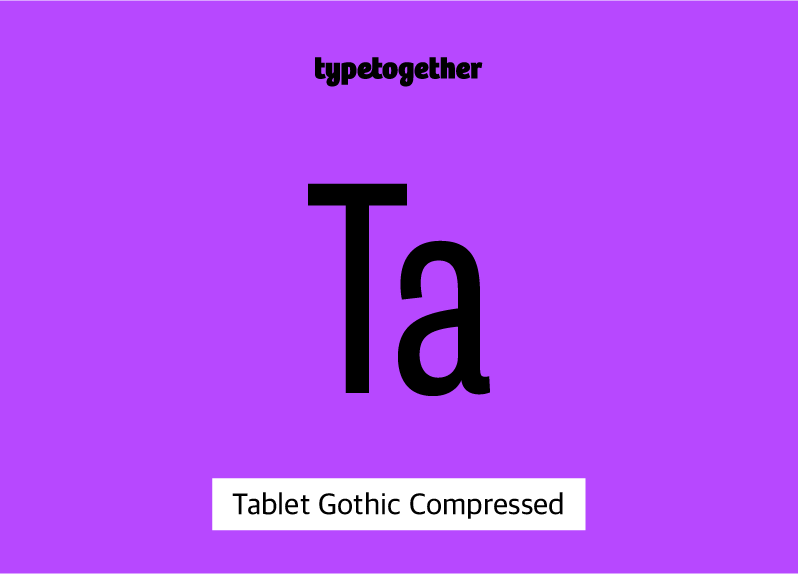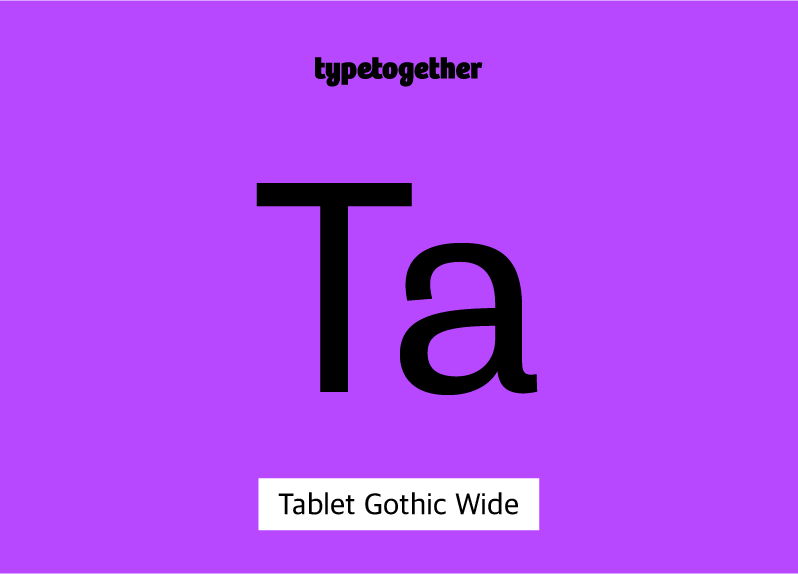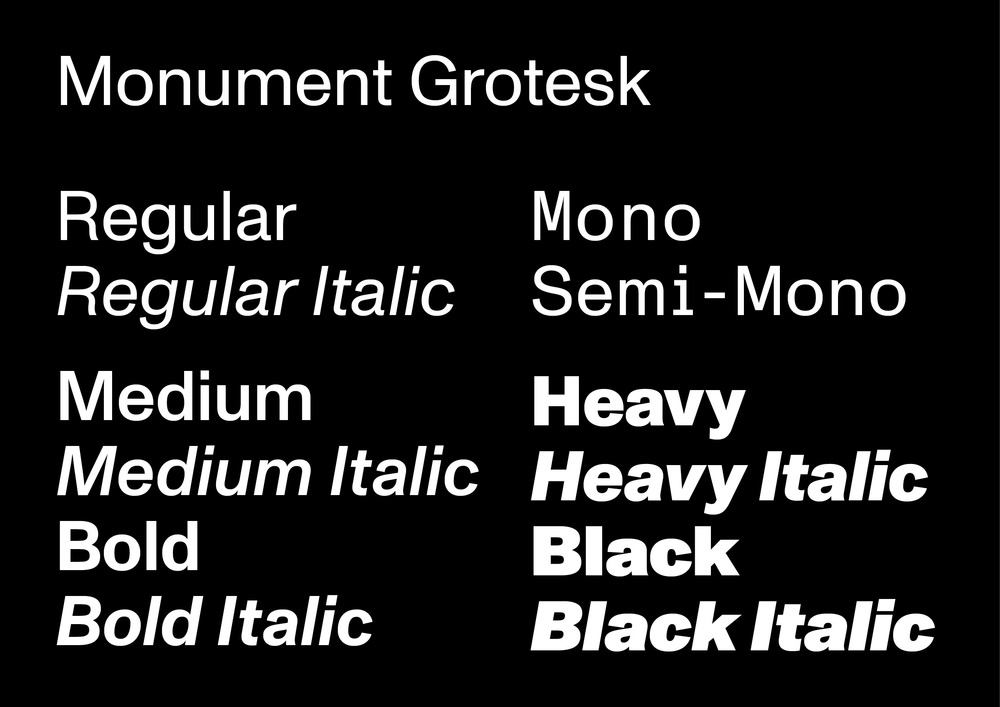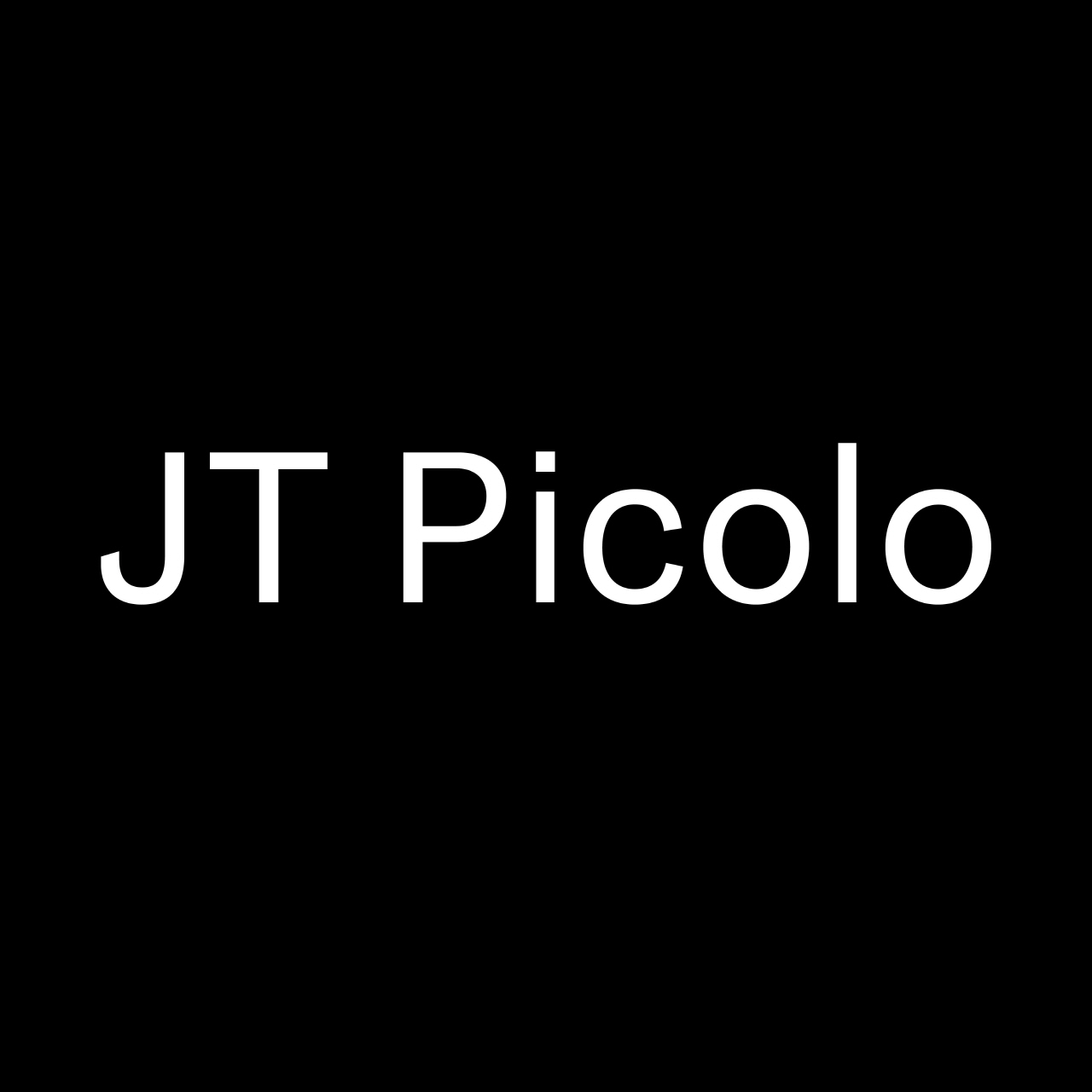
깔끔한 디자인의 완성
뉴트럴한 라틴 산세리프 폰트 추천
살면서 딱 하나의 폰트만 쓸 수 있다면?
많은 분들이 비슷한 폰트를 떠올리셨을 것 같은데요.
혹시 깔끔하고 질리지 않는 산세리프 폰트를 선택하지 않으셨나요?
산세리프 폰트 하나만 잘 골라도 디자인이 쉽게 완성되는 걸 느껴보셨을 거예요.
중립적인 인상이라 다 똑같다는 생각은 금물! 뉴트럴한 폰트들도 미세한 차이로 각기 다른 매력을 발산하는데요.
산돌구름에서 특별히 엄선한 폰트들을 지금 소개해 드릴게요.
네오-그로테스크가 뭐지?
오늘 소개할 폰트들은 네오-그로테스크(Neo-Grotesque)라는 계열로 분류되는 라틴 폰트들입니다.
글자의 장식적이거나 투박한 요소를 다 덜어내고 정제하여 깔끔한 인상이 특징이죠.
대표적인 폰트로는 헬베티카(Helvetica), 유니버스(Univers), 에리얼(Arial) 등이 있는데요.
산돌구름에서 만나볼 수 있는 현대적인 인상의 네오-그로테스크 계열 폰트를 알아볼까요?
디나모
ABC Monument Grotesk
「ABC Monument Grotesk」는 스위스 파운더리 디나모에서 만든 폰트입니다. 디나모는 2016년에 스위스 연방 문화청으로부터 스위스 디자인 어워드를 받을 정도로 실력을 인정 받았고, 국내에서도 많은 팬을 보유하고 있어요. 「ABC Monument Grotesk」 는 디나모의 초기 설립 때부터 함께한 대표 폰트 중 하나랍니다.
「ABC Monument Grotesk」는 출판물, 사이니지, 포스터, 패키징 등등 매체와 사이즈를 가리지 않고 두루두루 쓰이고 있습니다. 별다른 그래픽 요소 없이도 글자의 형태와 리듬감 자체를 한껏 살린 디자인에 특히나 멋지게 어울려요. 각 글자들은 정직하고 개성 넘치는 형태를 특징으로 하며, 전형적인 네오-그로테스크 계열보다 약간 더 강조된 획대비가 매력적인 질감을 선사합니다. 하지만 모든 글자 전반의 조화로운 균형이 안정적인 글줄을 형성하여 모던한 인상을 줍니다. 폰트 하나만으로 전체 디자인의 완성도를 확! 높혀주는 것을 확인할 수 있죠.
고정폭 버전인 「ABC Monument Grotesk Mono」와 고정폭 폰트의 디자인 컨셉을 차용했지만 사실 완전한 고정폭 서체는 아닌 「ABC Monument Grotesk Semi-Mono」 패밀리도 있어 더욱 다양한 룩에 맞게 활용할 수 있는데요. 모노스페이스의 기계적인 느낌은 살리면서도 본문 조판에도 적합한 폰트를 찾고 있다면, 「ABC Monument Grotesk Semi-Mono」를 한 번 활용해 보시는 것을 추천드립니다.
플레이타입
Studio6
「Studio6」는 덴마크 파운더리 플레이타입에서 제작한 네오-그로테스크 산세리프 폰트입니다. 이 폰트는 획의 끝 부분이 수직 수평으로 깔끔하게 잘리도록 처리되어 더욱 정돈된 느낌을 줍니다. 로만과 이탤릭 각각 9종의 굵기를 제공하여 총 18종의 탄탄한 구성을 갖춘 패밀리랍니다.
이 폰트는 작게 보면 모든 획의 굵기가 균일해 보이지만, 크게 자세히 보면 획과 획이 만나는 부분이 미세하게 좁아지도록 디자인된 것을 볼 수 있어요. 이는 작은 크기에서는 획이 뭉쳐 보이는 것을 방지하고, 큰 크기에서는 독특한 디자인 요소로 작용할 수 있는 매력적인 디테일입니다.
다양한 패밀리 구성
네오-그로테스크 폰트는 다양한 너비와 굵기를 갖춘 방대한 패밀리로 사용자들에게 폭넓은 선택권을 제공하며 큰 인기를 얻었습니다. 다양한 용도에 맞게 활용할 수 있어, 프로젝트에 맞는 최적의 선택을 할 수 있도록 도와줍니다.
산돌구름에도 이렇게 다양한 패밀리를 갖춘 폰트들이 많이 있는데요. 한번 살펴볼까요?
더타입파운더스
Shapiro
「Shapiro」는 더타입파운더스에서 제공하는 폰트로, 7개의 서브 패밀리로 나뉘어서 제공되는데요. 패밀리의 이름을 자세히 보면 각기 특화된 용도에 알맞게 디자인 되어 있다는 것을 알 수 있습니다.
기본 버전인 「Shapiro」는 자간이 적당히 넉넉하게 적용되어, 작은 사이즈에 긴 글줄로 조판했을 때도 갑갑해 보이지 않아 본문용으로 쓰기에도 알맞은 패밀리에요. 「Shapiro Headline」과 「Shapiro Display」는 좀 더 큰 크기의 헤드라인이나 디스플레이 용도로 사용되기 적합하도록 자간이 조금 더 좁게 조정된 패밀리입니다. 글자의 수가 적다면, 자간을 좁게 설정하는 것이 덩어리감을 더해 주어 주목성을 높일 수 있기 때문이죠. 「Shapiro Max」는 이런 좁은 자간을 최대치로 적용하여, 공간을 아주 큰 크기의 글자로 채워야 할 때 쓰일 수 있도록 설계했어요.
「Shapiro」는 위에 소개한 패밀리 외에도 굉장히 두꺼운 굵기 2종을 제공하는 「Shapiro Base」, 넓은 폭의 「Shapiro Wide」, 그리고 좁은 폭의 「Shapiro Pro」까지 다양한 서브 패밀리들로 구성되어 있어요. 베리어블 폰트로도 만나볼 수 있으니, 미세한 웨이트 조절이 가능해 훨씬 더 유용하게 쓸 수 있답니다. 선택의 폭은 무궁무진하겠죠?
타입투게더
Tablet Gothic
「Tablet Gothic」은 사용자들의 눈에 가장 익숙한 비율일 「Tablet Gothic Wide」 부터 매우 좁은 너비의 「Tablet Gothic Compressed」 까지 무려 6개의 다양한 너비를 제공하는 폰트 패밀리인데요. 한정된 공간에 많은 양의 정보를 조판해야 한다면 특히나 유용하게 사용할 수 있는 폰트입니다.
「Tablet Gothic」은 차갑고 정제된 느낌의 네오-그로테스크보다는 약간 따뜻하고 투박한 느낌을 가진 초기 그로테스크 인상을 지니고 있는 폰트입니다. 대문자 I 가 위아래로 세리프를 가지고 있는 형태이고, 글자가 시작되는 상단 획의 끝부분이 약간 안으로 말려 들어간 대문자 G, C 그리고 소문자 r, a 등의 형태가 생동감을 더해줍니다.
이 폰트는 긴 글에 쓰였을 때 특히나 그 따뜻한 질감과 특유의 매력이 더 잘 느껴진답니다. 특히 다양한 위계가 필요한 잡지 등의 편집 디자인에서 빛을 발할 폰트입니다. 강조가 필요한 곳에는 두꺼운 굵기로, 소제목은 좁은 너비와 대문자의 조합으로 조판해 보는 건 어떨까요? 통일된 느낌을 주면서 지면에 풍부한 느낌을 더할 수 있을 거에요. 「Tablet Gothic」 은 특히 숫자도 매력적으로 디자인되어 있어, 디자인 요소로 꼭 활용해 보시길 권해드립니다.
더 특별한 것을 찾고 있다면?
기본적인 형태는 중립적인 인상을 가지고 있지만, 어딘가 독특한 포인트가 있는 폰트를 찾고 있다면 주목해 주세요.
줄라이타입
JT Picolo
「JT Picolo」는 7월에 새롭게 입점한 따끈따끈한 신생 파운더리, 줄라이타입의 폰트입니다. 다양한 용도로 두루두루 무난하게 활용할 수 있는 폰트로 추천드려요. 키릴과 그릭도 포함되어 있어 다국어 환경에도 걱정 없이 쓸 수 있는 폰트입니다.
「JT Picolo」의 숨은 매력은 오픈타입 피쳐를 활용한 대체 글립에 있습니다. r과 g 글자를 대체 글립으로 바꾸기만 해도, 완전히 다른 느낌을 연출할 수 있어요. 흰색 티셔츠가 여러 개 있어도 사소한 디테일 때문에 손이 가는 게 있듯이, 「JT Picolo」도 계속 찾게 되는 은근한 매력이 있답니다.
제타폰트
Milligram Roman
마지막으로 소개해 드릴 제타폰트의 「Milligram Roman」은 네오-그로테스크 뼈대를 기본 바탕으로 하면서도, 어딘가 귀여운 인상의 소문자 a 와 독특한 패밀리 구성을 가지고 있는 폰트입니다.
「Milligram Roman」은 편안하게 읽혀 본문 등 다양한 용도로 활용하기에 적합한 반면, 「Milligram Macro」 스타일은 극단적으로 좁은 자간을 가지고 있어 디스플레이 용도에서 강렬한 느낌을 내기 딱이에요. 자간이 타이트하다 못해 글자와 글자가 거의 붙어 있는 것을 볼 수 있는데요. 이런 특징을 적용한 폰트는 보기 드물어 꼭 소개해 드리고 싶었답니다. 크게 짧은 글줄로 쓰는 제목이나 단어 몇 개 등을 강조할 때 한번 써 보세요.